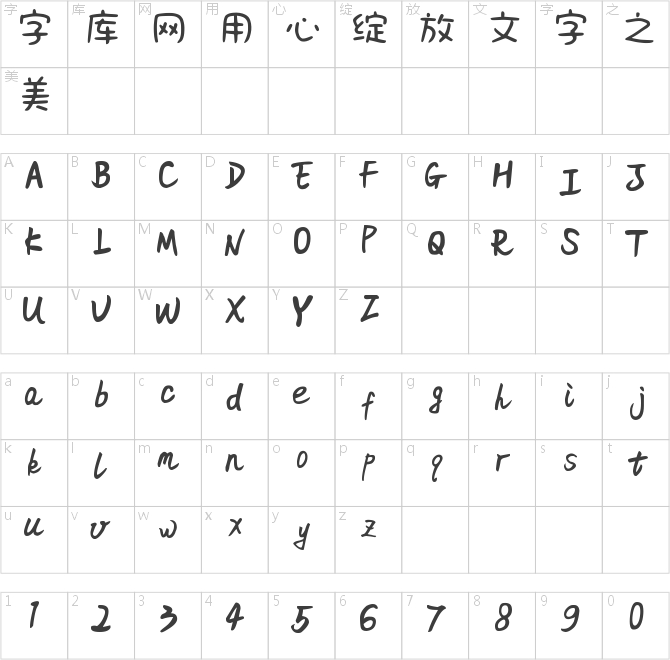
鼎獵萌娃體 詳情頁
﹤p﹥“鼎獵視界”微信公眾號(dingliesky),各類符合資質(zhì)的幼兒園和小學(xué)(個人非營 利范圍內(nèi)永久免費使用)。﹤/p﹥鼎獵萌娃體字體字庫是一款讓人賞心悅目、百看不厭的中文字體,適合各類廣告和產(chǎn)品包裝設(shè)計應(yīng)用,字體大小5.22MB,格式為ttf字體,上傳用戶是東情,作者/版權(quán)方為鼎獵